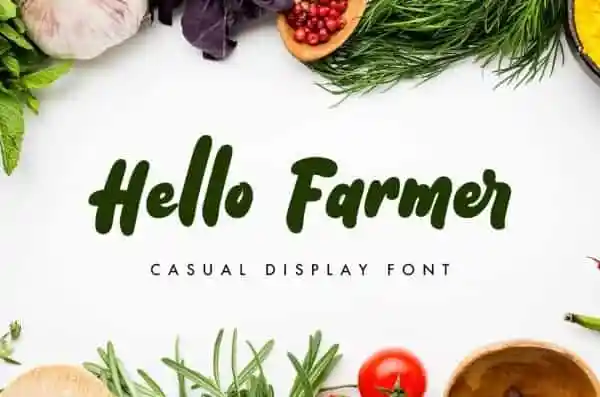
Hello Farmer Display Font – Download Grátis
A fonte “Hello Farmer Display Font” é uma mão-dada criada por Nurf Designs com um toque delicado, perfeita para aqueles projetos que exigem alegria e simplicidade. Especialmente adaptada para design promocional, rótulos, embalagens, identidades de marca e logotipos, esta fonte apresenta um estilo de escrita infantil e encantador. Seu uso em diversos formatos é um prato cheio, sejam eles textos corporativos ou lindas ilustrações para a sua próxima coleção de produtos. A “Hello Farmer Display Font” oferece suporte à maioria dos caracteres multilingue e inclui letras maiúsculas, minúsculas, números, pontuação e ligaduras criativas. Com um design tão delicado e encantador como esta fonte, certamente agradará tanto aos estilistas gráficos quanto às marcas que buscam manter seu estilo único em cada projeto. Descarregue agora “Hello Farmer Display Font” e revigore seus projetos com esse toque de simplicidade e criatividade. Estamos ansiosos para vê-lo no seu próximo design!